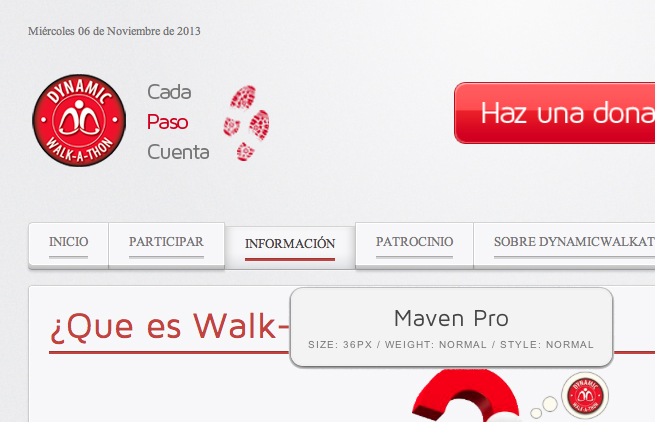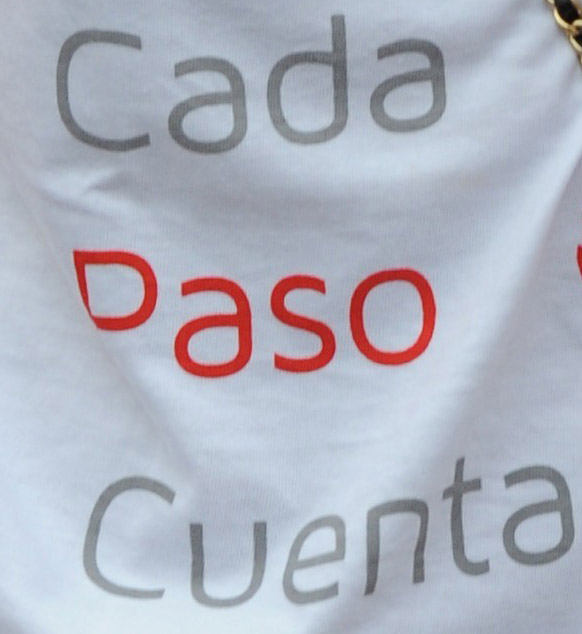
Suche sehr dringend diese minimalistische Sans serif
Habe schon alle gängigen Tools verwendet und noch manuell ca. 4000 Sans abgeglichen, ohne nennenswerten Erfolg. Titanium Regular weist Ähnlichkeiten auf, hat aber nicht den gleichen humanen und positiven Touch. Brauche also wohl den exakten Schnitt.
Das Bild stammt von einer Sportaktion ("Jeder Schritt zählt"), wohl so eine Art Marathon für viele Leute. Wird uns nicht weiterbringen.
Wie bist du vorgegangen? Hattest du den Namen in Erinnerung oder wie sucht man sowas am besten?
… wie sucht man sowas am besten?
Ich hab den Dateinamen deines Bildes angeschaut (irgendwas mit Marbella Charity Walk Sylvie van der Vaart) und nach diesen Stichpunkten gegoogelt. Das ergibt dann die homepage http://www.dynamicwalkathon.com – dort ein wenig herumgesurft, bis ich den Font als Schrift und nicht als Bild hatte. Fount hat mir dann verraten, welcher Font das ist. Wenn man weiß wie’s geht, ist es leicht ;-)